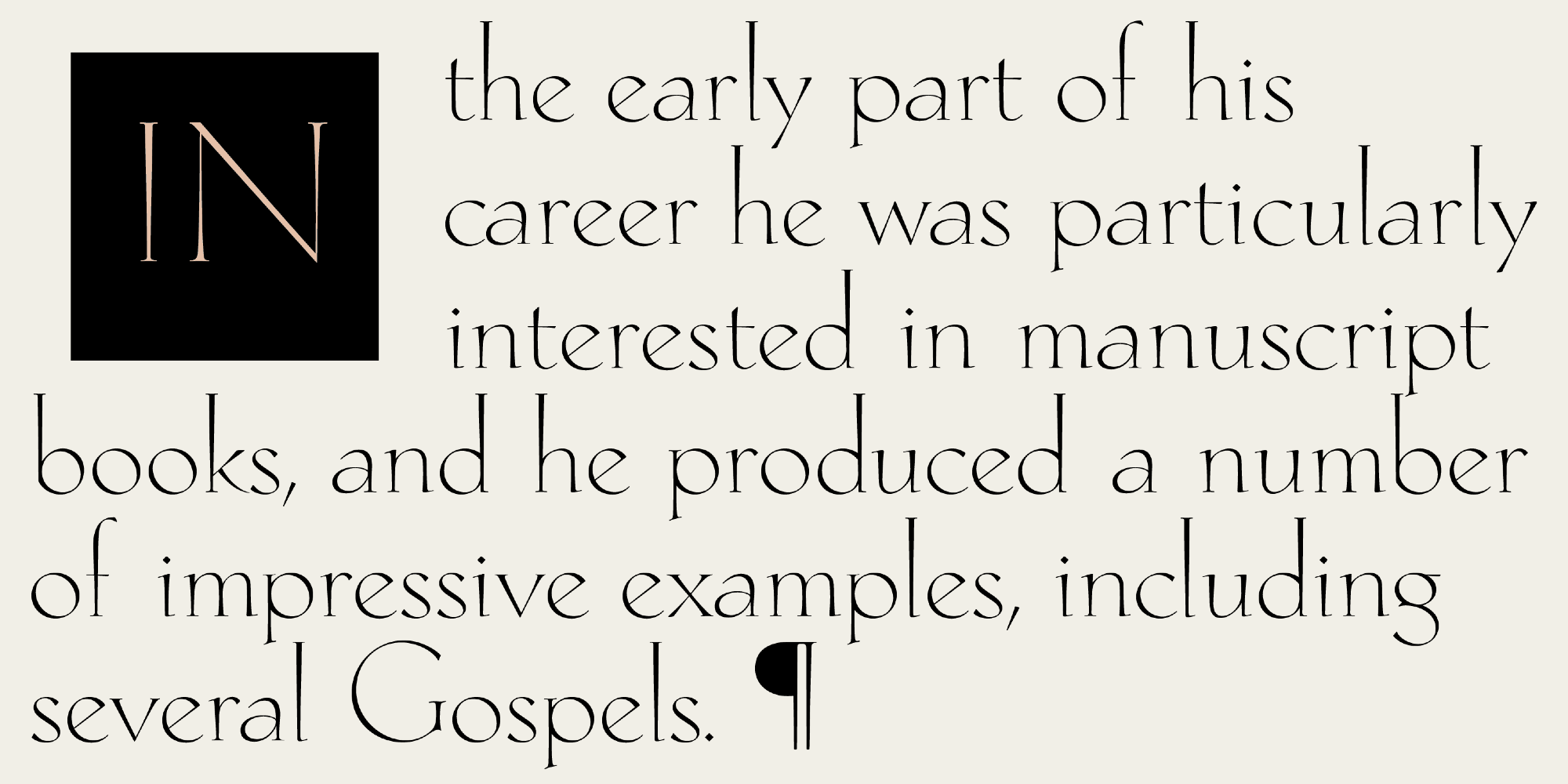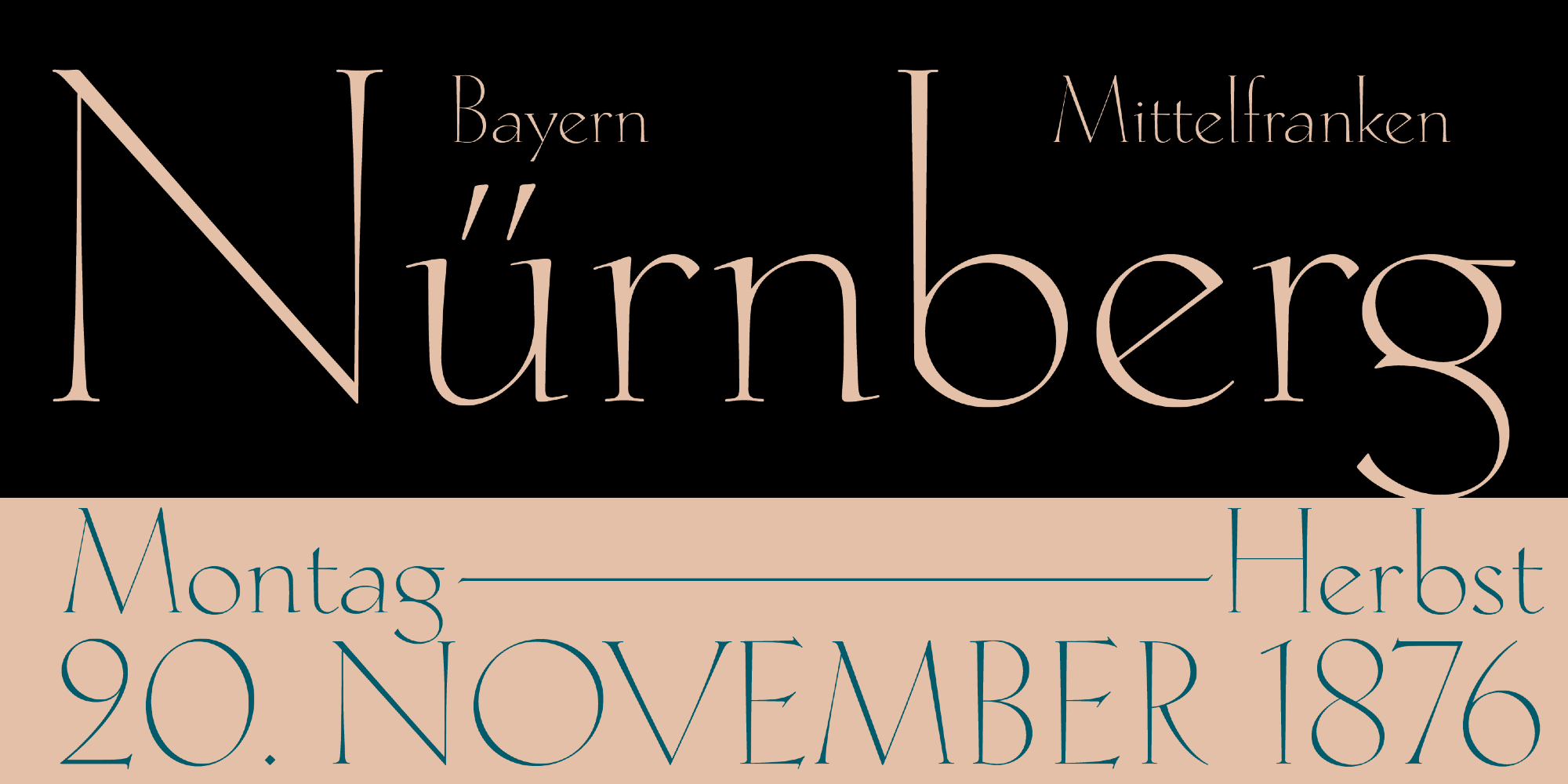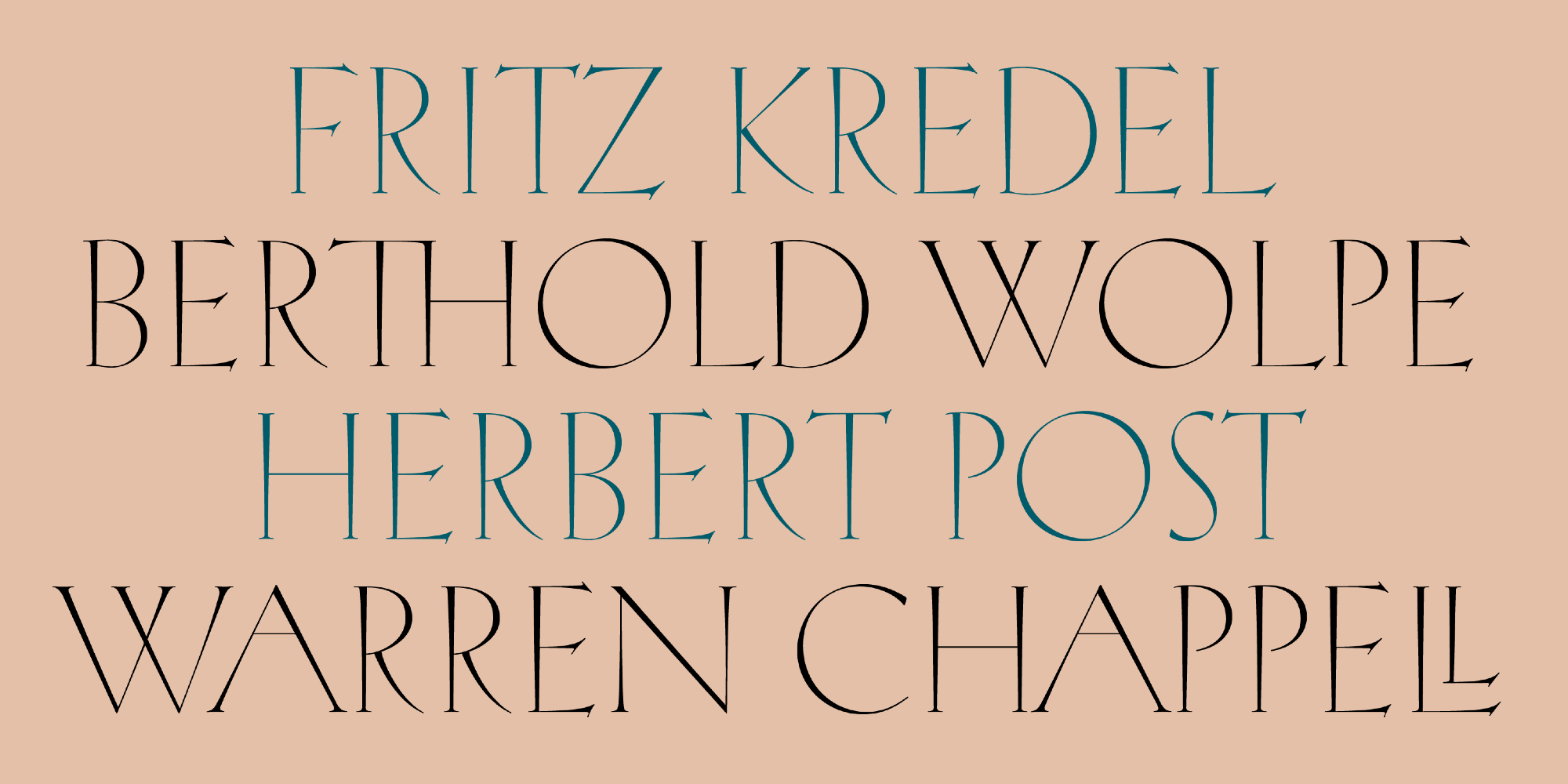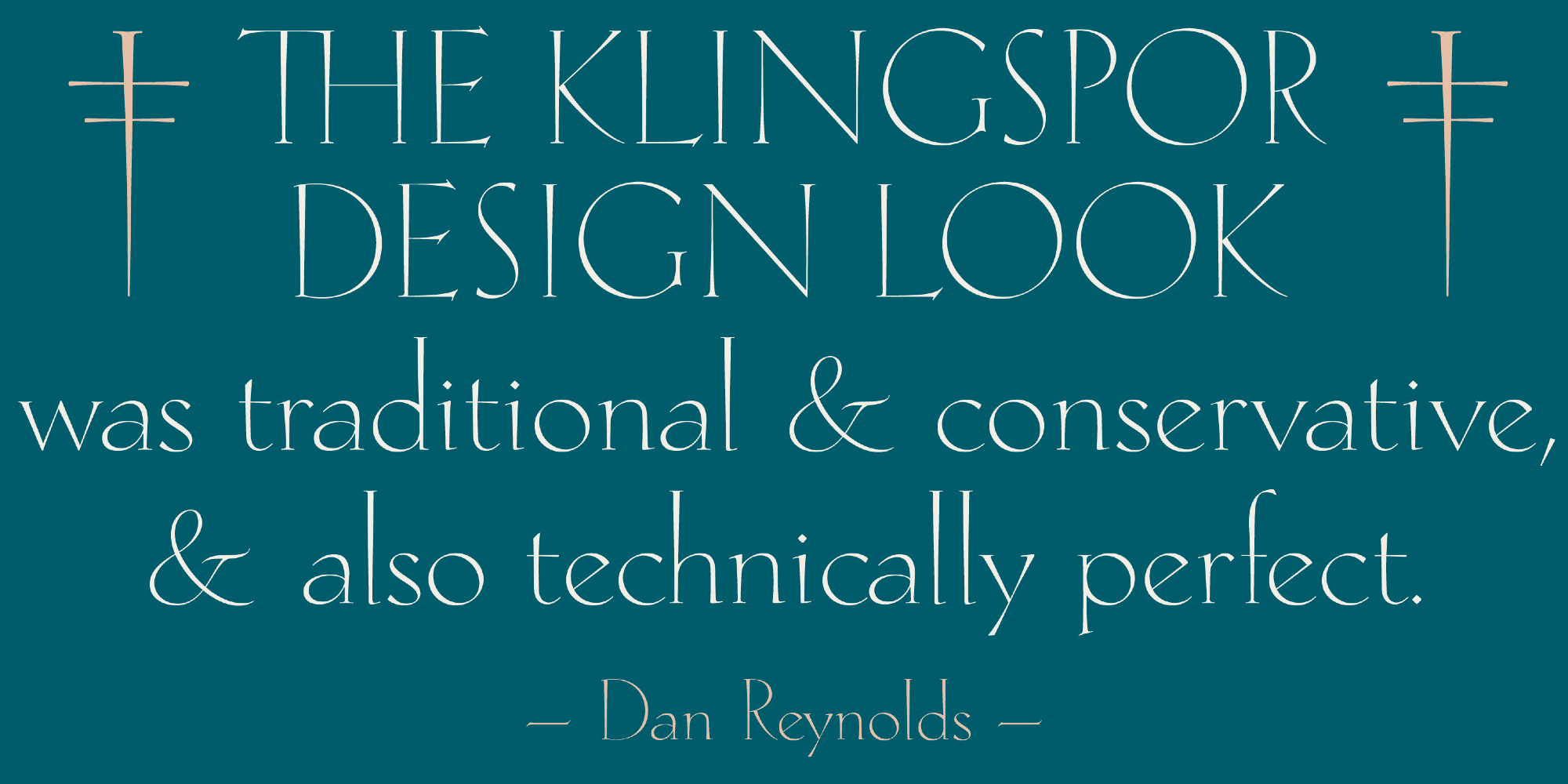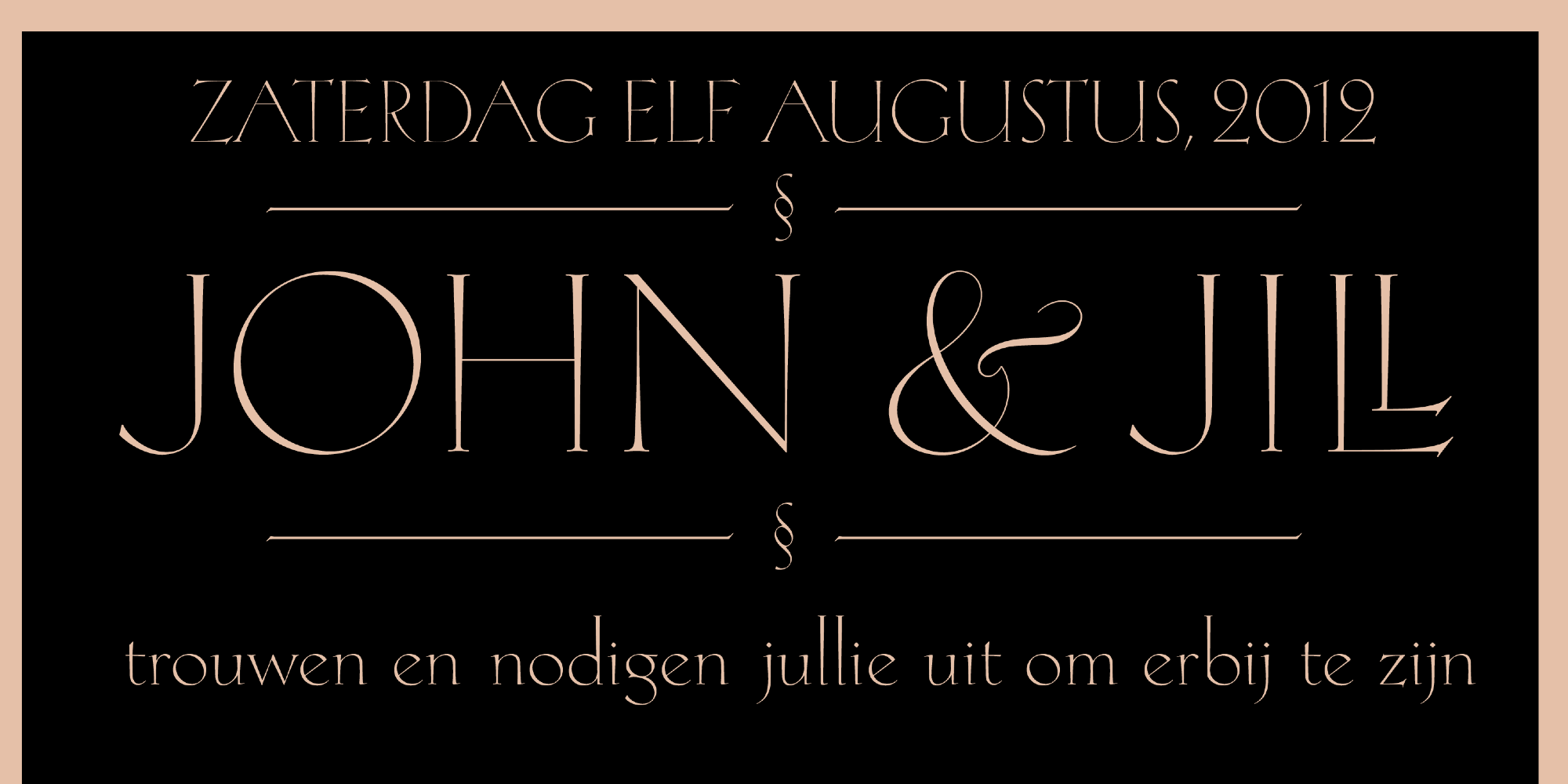
• Serifen:
• serif
• Antiqua humanistisch
• Versaleszett:
• enthalten
Die Rudolf Antiqua von Vater und Sohn Claudio Rocha und Lucas Franco ist eine moderne Adaption des mageren Schnitts von Rudolf Kochs Koch-Antiqua. Die Schrift ist weniger eine Digitalisierung als eine Neuinterpretation. Die Schrift entstand bereits in den 2010er-Jahren als Teil einer größeren Familie auf Basis der Koch-Antiqua. Bislang wurde jedoch nur der magere Schnitt über CAST veröffentlicht. Die Schrift verfügt neben der herkömmlichen westeuropäischen Belegung auch über Buchstabenvarianten mit kurzen Oberlängen und zahlreiche Schmuckligaturen.